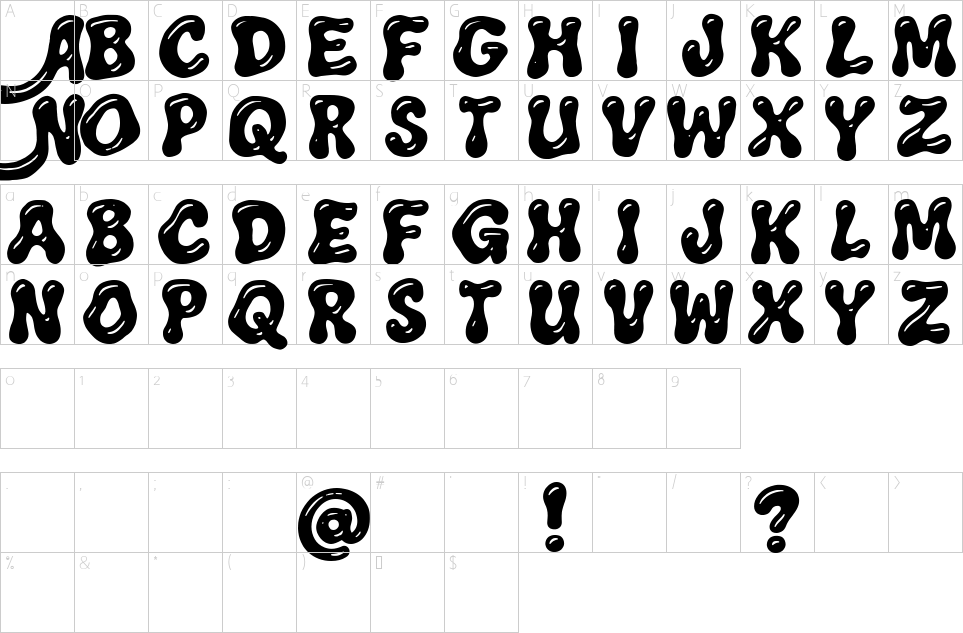
A fonte Acidrop oferece um toque único e alegre para seus projetos digitais. Designada por The Branded Quotes, esta font é perfeitamente adaptada para aplicações que buscam um estilo descontraído e divertido. Com seu design criativo, ela adquire um charme especial, tornando-a uma escolha popular para designers e desenvolvedores de sites. Recentemente, a font foi baixada 482 vezes, demonstrando seu valor e popularidade em meio a uma vasta variedade de opções de fontes gratuitas. Com a Acidrop, você pode adicionar um toque especial a seus documentos e sites, oferecendo um design agradável e único.